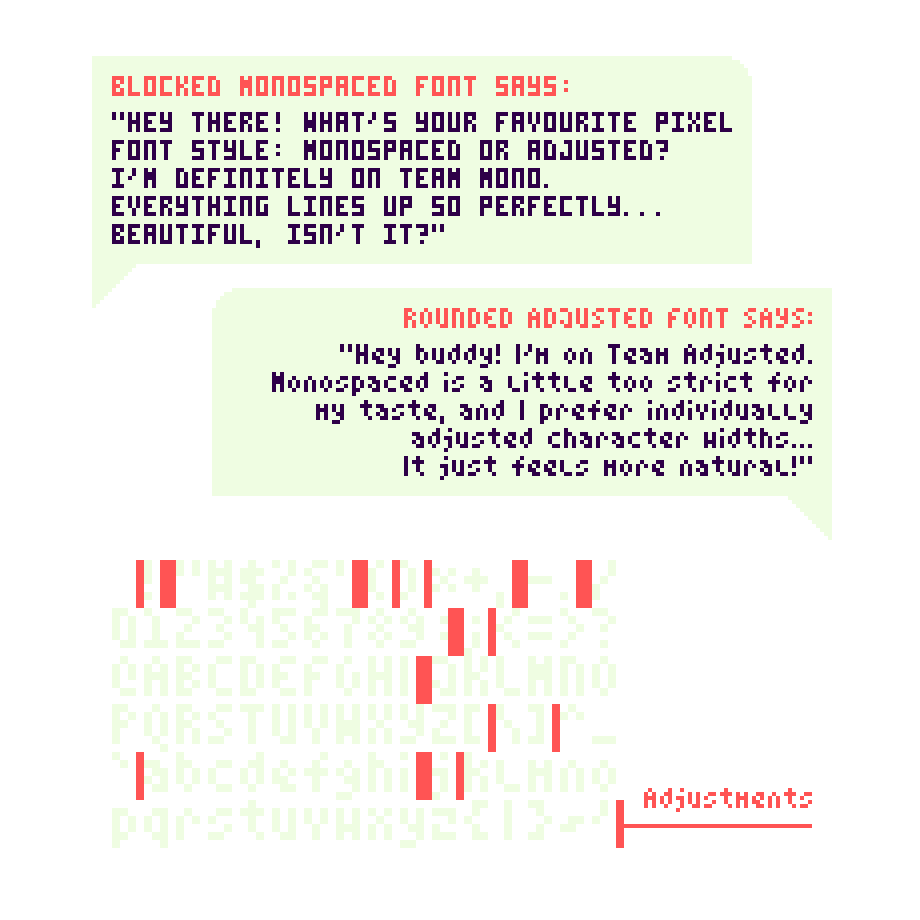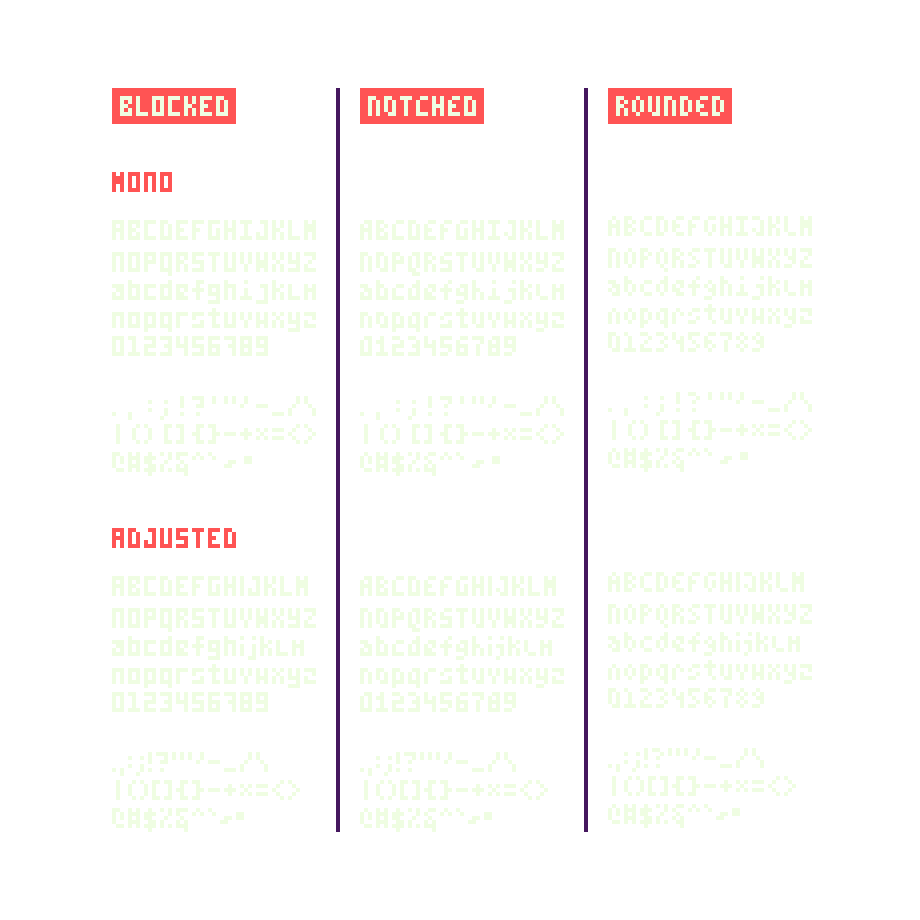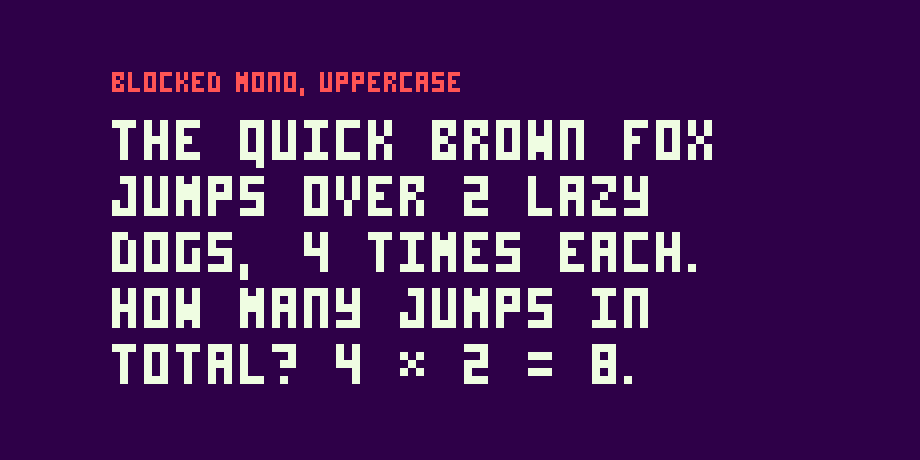
6种不同的3*5像素等宽字体素材,包含六款 3×5 像素 TTF 格式字体的合集,共有三种样式,每种样式均提供等宽版和调整版。
Blocked风格严谨且基于网格;Notched风格更具特色;Rounded风格则更柔和。这一系列风格用途广泛,适用于游戏 UI 和低分辨率项目中的小文本。
等宽版本采用真正的等宽字体,每个字形都使用相同的字符宽度。调整版本则使用单独调整的宽度和间距,以获得更平衡的视觉效果。
支持字符:97 个字符,包括专用大写字母和小写字母、数字、标点符号和常用数学符号。